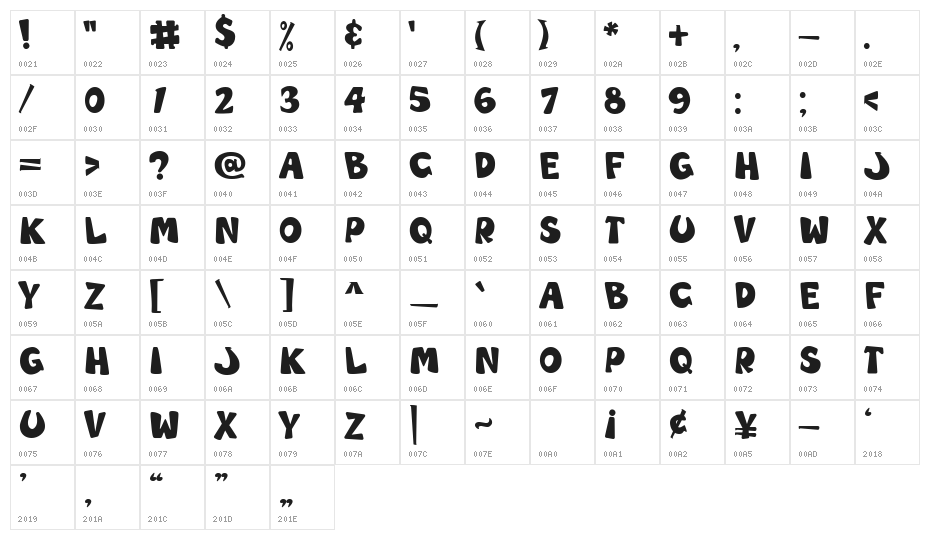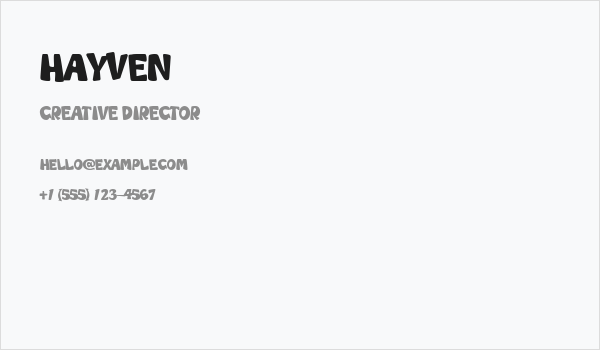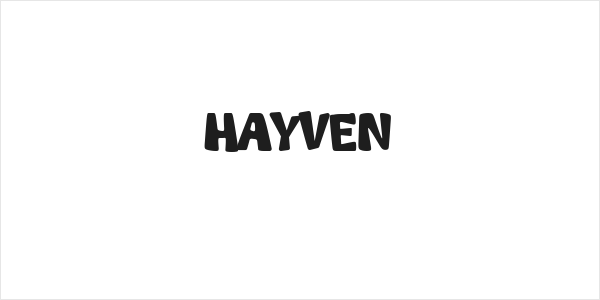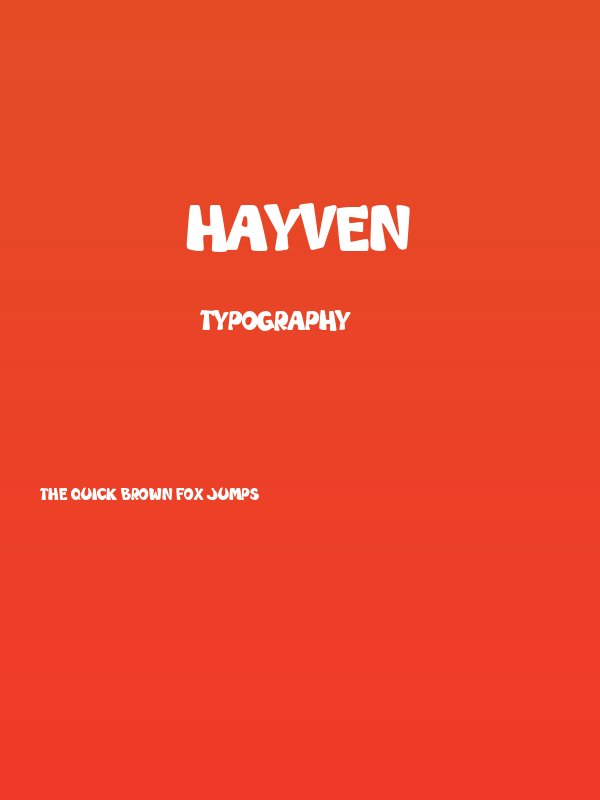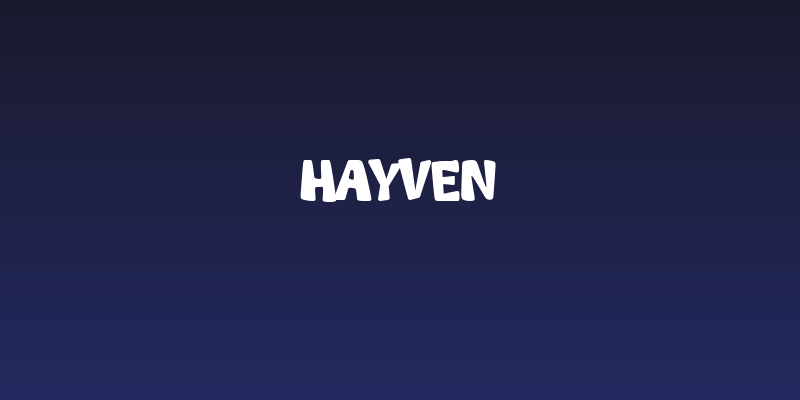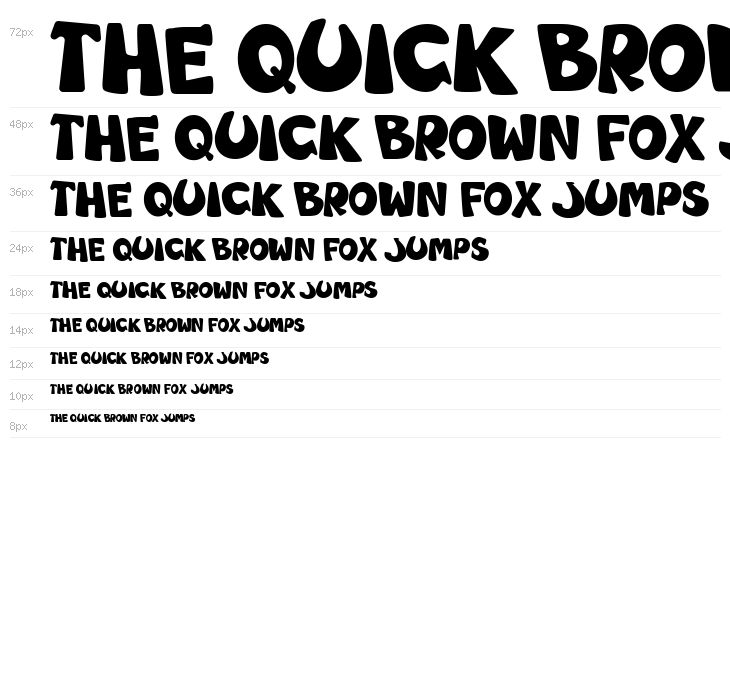
Hayven Font
✎ Cartoon
| Kategorien | Cartoon |
| Gesamtstil | Playful, Comic |
| Anwendungsfall | Headlines, Posters, Branding |
| Vorgeschlagene Projekte | Ideal for children's books, comic strips, playful branding, and eye-catching posters. |